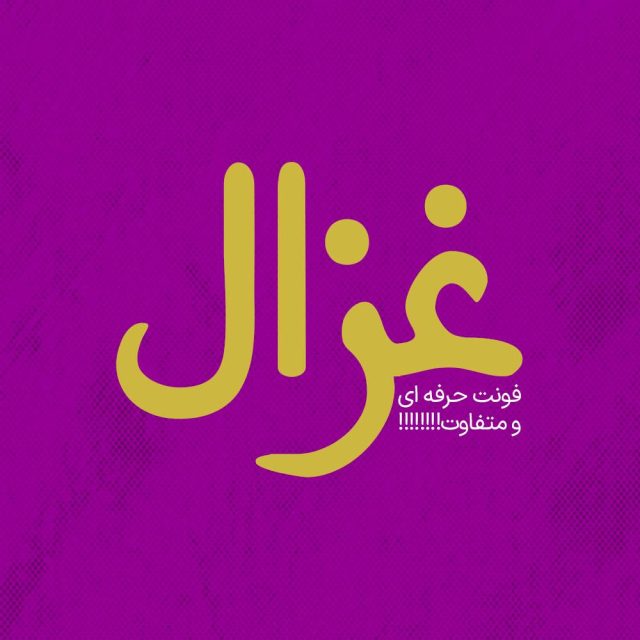
فونت فارسی غزال Ghazal Font
فونت فارسی غزال یک فونت تک وزن با سبک دستنویس و با کاربرد طراحی امضا، لوگوتایپ و طراحی های مختلف همچون کتاب و تولید محتوای متن…
فونت فارسی غزال یک فونت تک وزن با سبک دستنویس و با کاربرد طراحی امضا، لوگوتایپ و طراحی های مختلف همچون کتاب و تولید محتوای متن های کوتاه و عناوین می باشد. این فونت با ساختار حروف خود مناسب استفاده در لوگوهای نوشتاری می باشد. همچنین از این فونت در طراحی تابلوهای چلنیوم هم به دلیل ساختار منحصر به فردش می توانید استفاده کنید. در ادامه برای شما نمونه تایپ های این محصول حرفه ای رو آماده کردیم که میتونید مشاهده کنید.
• مناسب طراحی بسته بندی ها و چاپ
• فونت ویژه تبلیغات محیطی
• فونت طراحی کاور اینستاگرام
• فونت حرفه ای برای تولید محتوا
• فونت فارسی طراحی وبسایت
• فونت طراحی لوگو تایپ فارسی
• مناسب استفاده در تابلو های چلنیوم و طراحی حروف
پیشنمایش و نمونه تایپ های فونت غزال